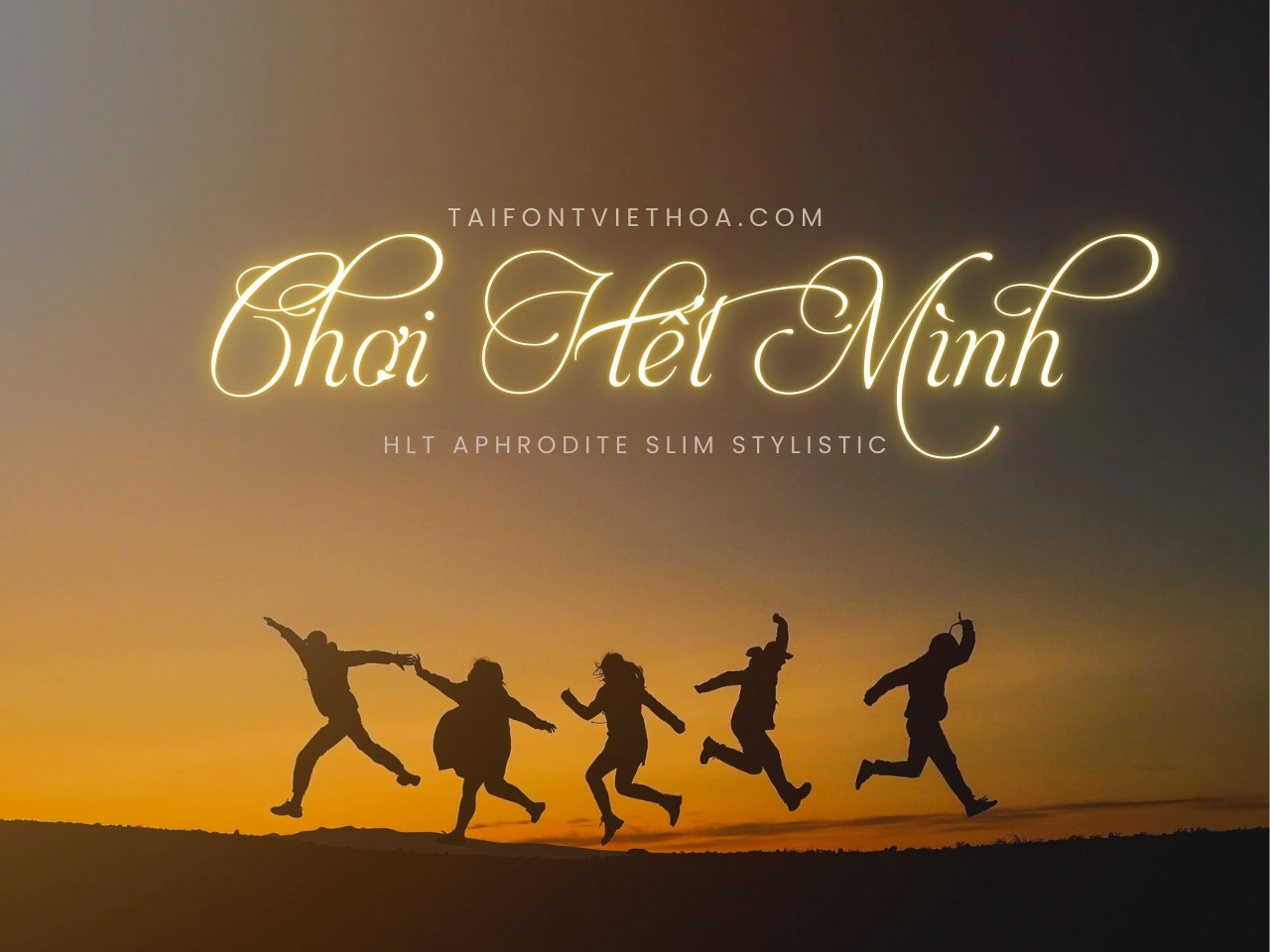
Giới thiệu về font HLT Aphroditeslimstylistic – Vẻ đẹp tinh tế của thư pháp hiện đại
HLT Aphroditeslimstylistic là phiên bản Việt hóa từ font gốc “Aphrodite Slim Stylistic” – một kiểu chữ script mang phong cách thư pháp được sáng tạo bởi nhà thiết kế Sabrina Mariela Lopez. Font được phát hành bởi hãng font Sudtipos, nổi bật với phong cách bay bổng, uốn lượn và đậm chất nghệ thuật, thường được dùng trong các thiết kế lãng mạn, thiệp mời và nhận diện thương hiệu cá nhân. Phiên bản gốc hỗ trợ hơn 50 ngôn ngữ Latinh, được ứng dụng rộng rãi trên toàn thế giới.
Bản Việt hóa được thực hiện công phu bởi nhóm HLT Fonts, đảm bảo đầy đủ các ký tự tiếng Việt với dấu chuẩn, giúp font có thể sử dụng linh hoạt trong các thiết kế dành riêng cho cộng đồng Việt Nam. Từ cách giữ nguyên ligatures (liên kết chữ cái) đến việc tinh chỉnh khoảng cách giữa các glyphs, bản Việt hóa của Aphroditeslimstylistic không chỉ đẹp mà còn cực kỳ hiệu quả về mặt thị giác. Font này hiện đã được taifontviethoa.com chọn lọc, kiểm thử thực tế và chia sẻ đến cộng đồng thiết kế Việt nhằm phục vụ các dự án sáng tạo cá nhân và chuyên nghiệp.
Đặc điểm thiết kế của HLT Aphroditeslimstylistic và ứng dụng thực tiễn
Font HLT Aphroditeslimstylistic sở hữu cấu trúc chữ uốn lượn duyên dáng, các đường nét thanh mảnh xen lẫn các điểm nhấn đậm tạo cảm giác linh hoạt và đầy biểu cảm. Hệ thống glyphs phong phú, đi kèm nhiều ligatures nghệ thuật giúp người dùng có thể tạo nên những đoạn văn bản mang tính cá nhân hóa cao. Các ký tự có đường nối mượt mà, rất phù hợp cho việc sử dụng trong các thiết kế cần sự mềm mại và nữ tính.
Font này phù hợp nhất trong các ứng dụng như thiệp cưới, bộ nhận diện thương hiệu thời trang, bìa sách lãng mạn, thiết kế bao bì mỹ phẩm cao cấp hoặc các chiến dịch truyền thông hướng đến khách hàng yêu thích sự tinh tế và sang trọng. Ngoài ra, HLT Aphroditeslimstylistic cũng được đánh giá cao khi ứng dụng trong thiết kế logo và đồ họa nghệ thuật cá nhân.